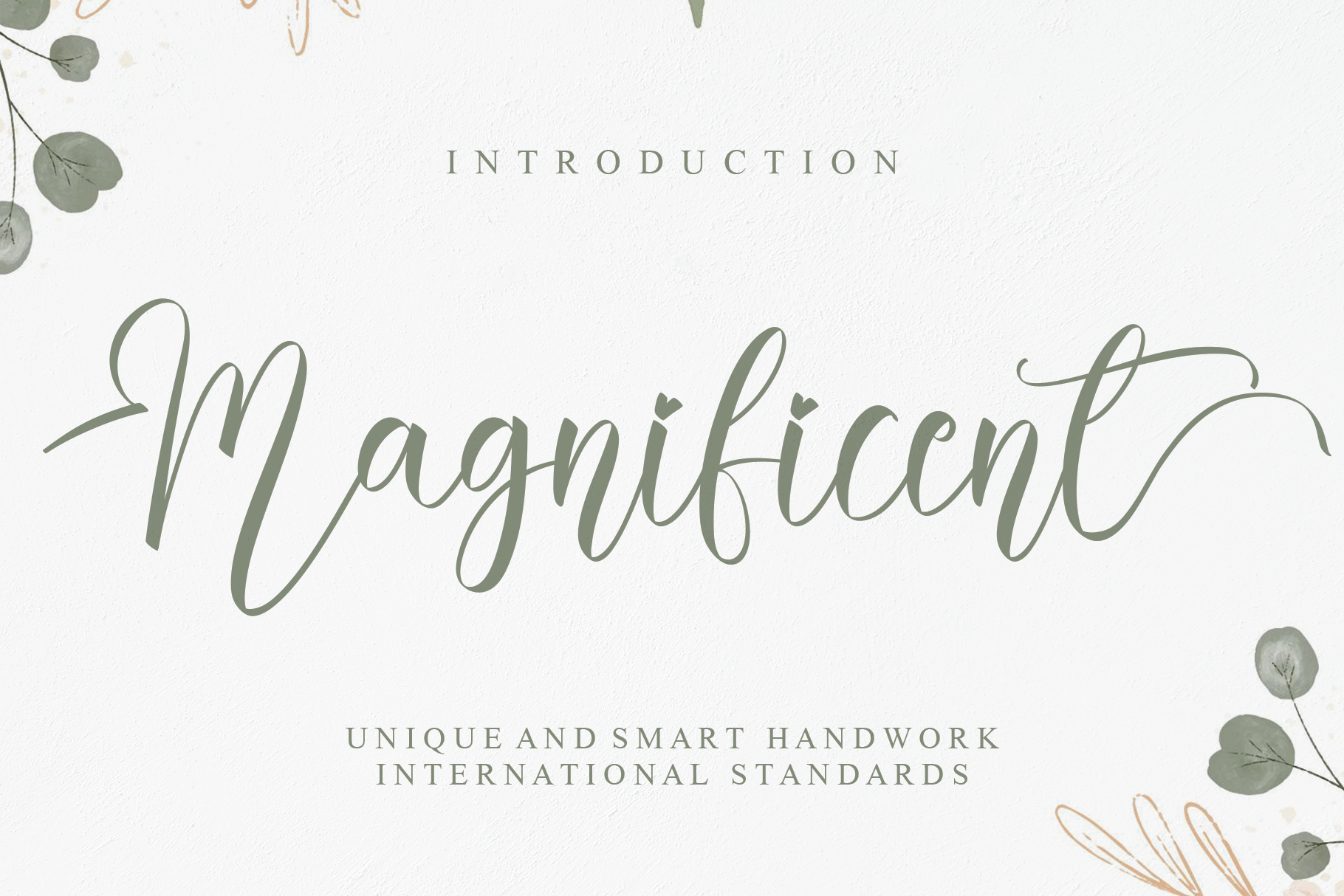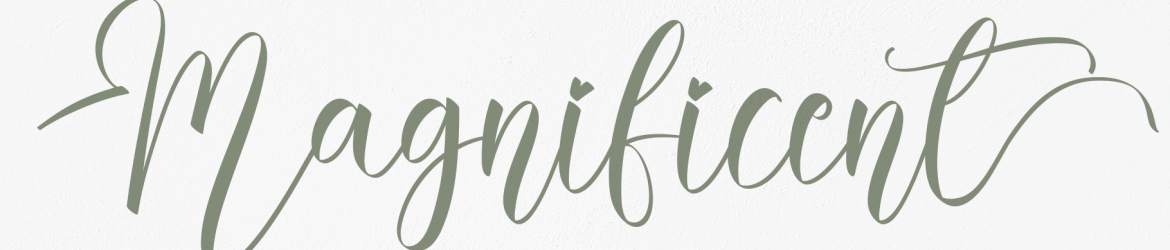
Magnificent Font é a escolha ideal para quem busca uma fonte de escrita à mão com estilo único para seus projetos criativos. Esta elegante família de caracteres tem sido concebida pensando nas necessidades dos designers e artesãos que buscam qualidade, originalidade e um toque diferenciado em cada projeto. O designer creativeletter trouxe uma coleção de letras escritas a mão perfeitas para diversos usos, desde publicações sociais até embalagens de produtos. Suas linhas suaves e traços delicados oferecem ao seu design um ar pessoal e único que pode transformar qualquer projeto em algo extraordinário. Magnificent Font está aqui para fornecer uma experiência excepcional aos usuários deste estilo, permitindo-lhes criar trabalhos de arte autênticos e atraentes. Com Magnificent Font, você tem à disposição uma fonte capaz de destacar seus projetos, independente do tipo de projeto que esteja envolvido. Seja para um post de rede social, uma campanha publicitária ou até mesmo uma etiqueta personalizada, esta fonte criativa é sua melhor opção. Compre Magnificent Font hoje e deixe seu design falar por si só com o toque especial da escrita à mão.